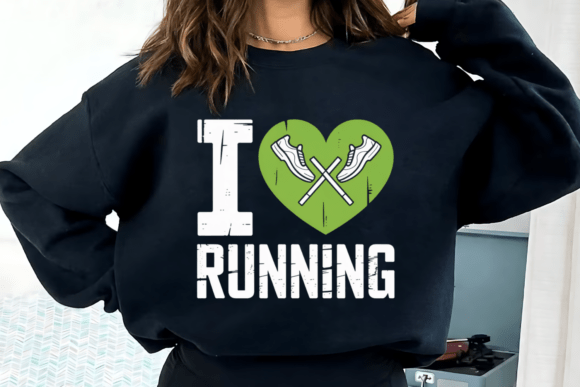
I Love Running Marathon Fitness PNG
Ulasan Detalhada: I Love Running Marathon Fitness PNG
Se você é apaixonado por corridas, maratonas ou simplesmente adora aquela sensação de liberdade ao calçar os tênis pela manhã, o design “I Love Running” chegou para transformar seu guarda‑roupa fitness. Com uma tipografia distressed e um coração verde cruzado por tênis de corrida, esta arte captura a energia, o movimento e a dedicação que todo corredor sente.
- Tipografia atlética desgastada que remete ao estilo vintage esportivo
- Ilustração icônica de coração de corrida com tênis cruzados
- Layout ousado e de alto contraste – destaca-se em qualquer cor de tecido
Se você busca um visual que una paixão pela corrida e estilo contemporâneo, o I Love Running Marathon Fitness PNG é a escolha ideal. Aproveite a energia desse design para criar peças únicas que inspiram você e sua comunidade a correr mais longe, mais rápido e com mais atitude.